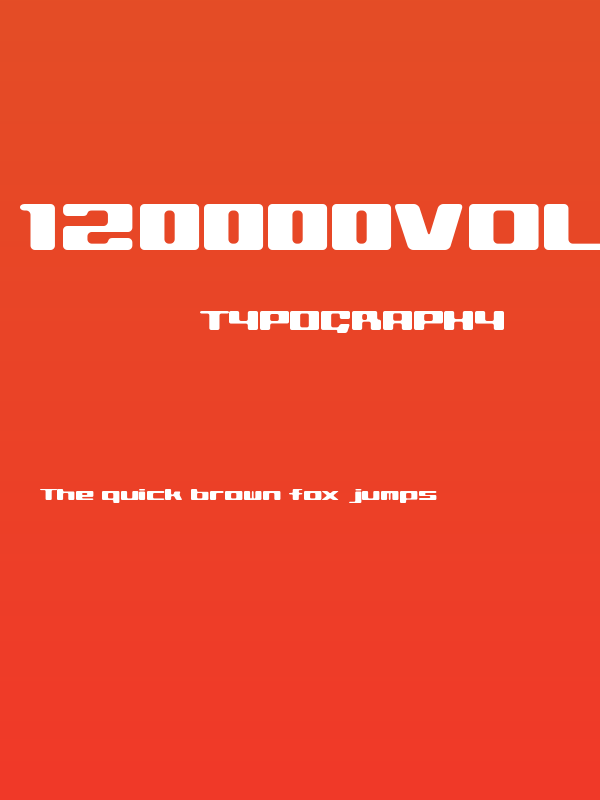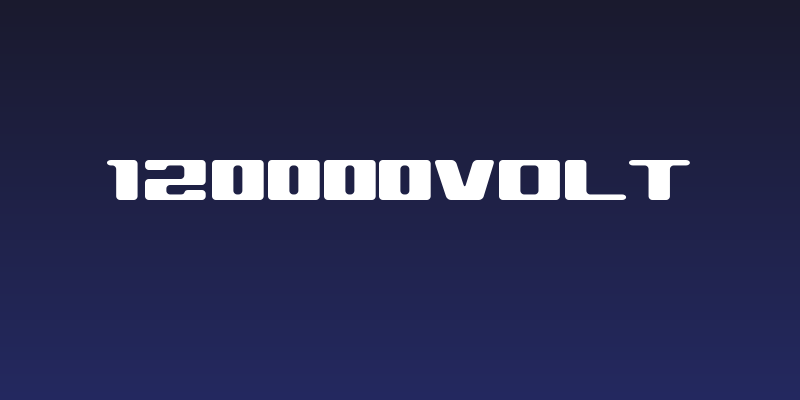
120000volt Font
| Larghezza | Expanded |
| Stile generale | Futuristic |
| Progetti proposti | Ideal for technology branding, sci-fi themed projects, video game titles, and posters that require a strong visual impact. |